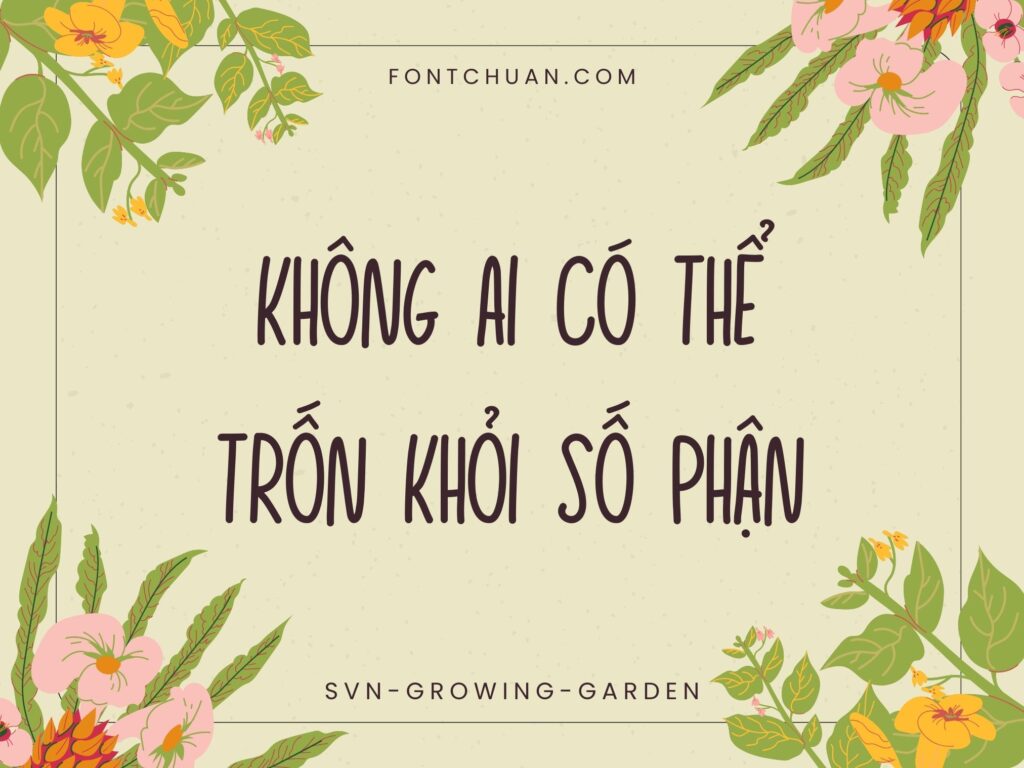
Font SVN Growing Garden Trọn Bộ + Dingbats Việt Hóa
Font SVN Growing Garden là phiên bản Việt hóa của kiểu chữ Growing Garden, được thực hiện bởi Styleno.1 Fonts. Growing Garden là một bộ ba phông chữ viết tay thanh lịch và tự nhiên, bao gồm các kiểu chữ Regular, Script và Dingbats. Phông chữ này mang lại vẻ ngoài độc đáo, phù hợp với nhiều ý tưởng sáng tạo như thiệp mời đám cưới, thiệp cảm ơn, trích dẫn, thiệp chúc mừng, logo, danh thiếp và các thiết kế cần đến nét viết tay.
SVN Growing Garden lý tưởng cho các dự án thiết kế yêu cầu sự cá nhân hóa và sáng tạo, như thiệp mời, logo và các ấn phẩm truyền thông. Các ngành nghề như thiệp cưới, ẩm thực và spa có thể tận dụng phông chữ này để tạo điểm nhấn trong thiết kế. Ngoài ra, phông chữ cũng thích hợp cho các sự kiện như Tết, Valentine, Sinh nhật và các lễ hội khác.